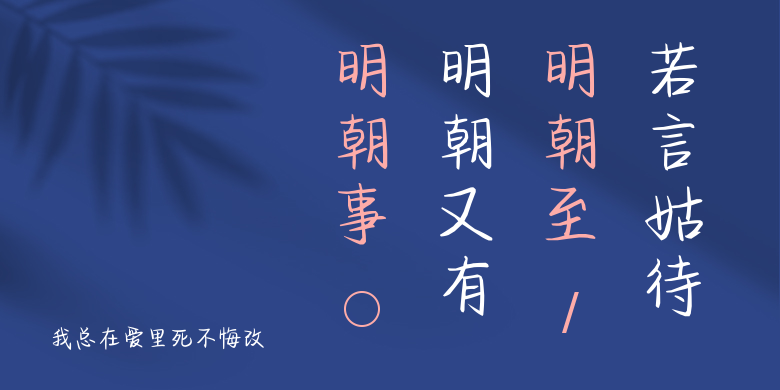
我总在爱里死不悔改
我总在爱里死不悔改,这款字体结构工整、笔画清晰,兼顾美观与易读性,适用于标题、正文、海报、包装、LOGO 等多种场景。字形优雅稳定,风格百搭耐看,适配日常排版与创意设计,让文字呈现更舒适、更具质感。我总在爱里死不悔改一笔一画,皆是细节,以均衡的比例、流畅的线条打造舒适视觉体验,字形端正大气,风格简约现代。无论是商业设计、品牌宣传还是日常排版,都能轻松驾驭,让文字更有格调与力量。我总在爱里死不悔改字体下载。